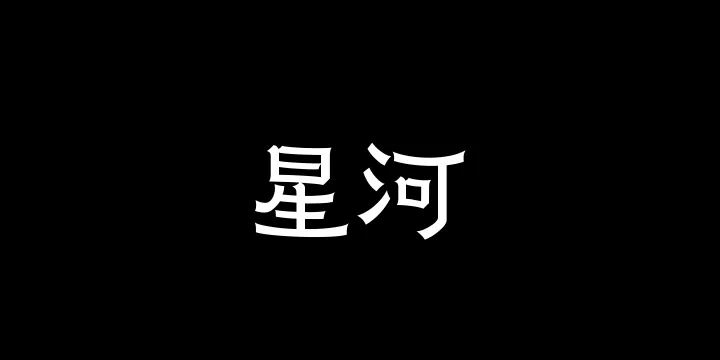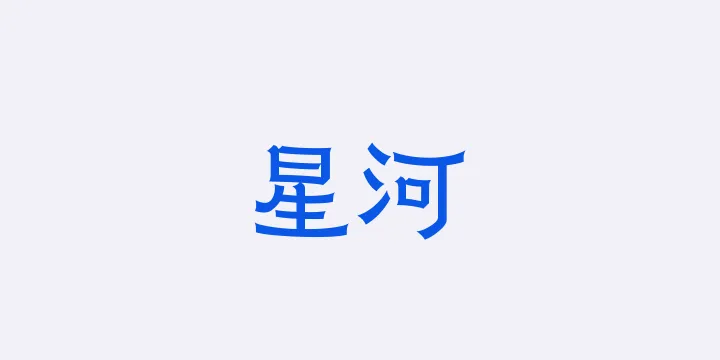
山海星河55W By 山海字库 商用字体
字体全名: 山海星河55W
字体简介: 山海星河55W,是一款全新风格的字体,是山海星河字体家族系列中的细款,编号55W,包含汉字9169个,符号200+个。该字体是一款具有强劲视觉冲击力的字体。字形结构多为方形结构,如正方形、长方形或扁方形,强调字形的稳定性。字形大小悬殊,通过大小不一的字来形成对比和层次感,造型硬朗,直线与曲线结合的笔画构成棱角分明、坚实有力。